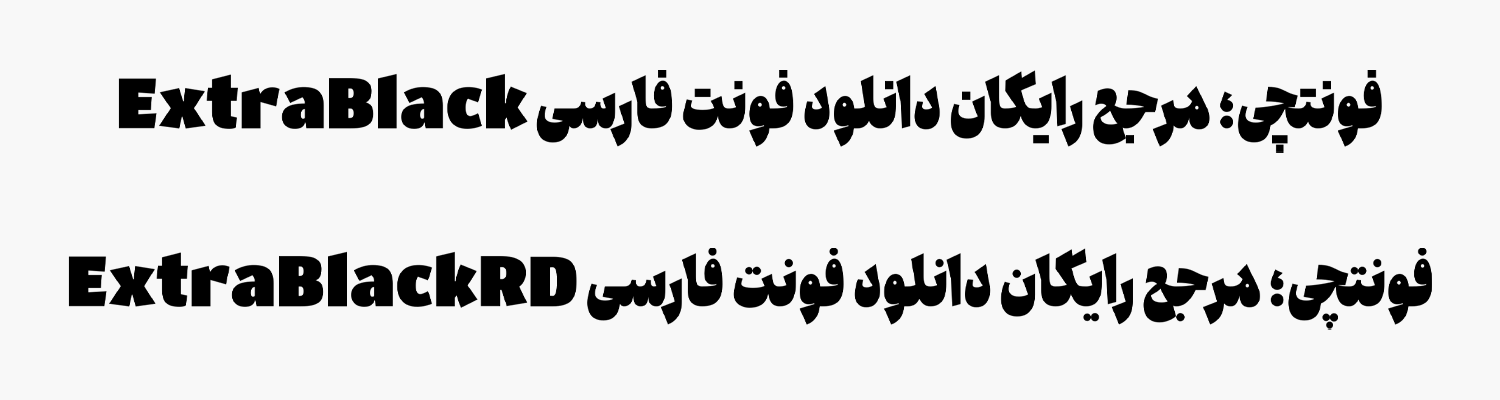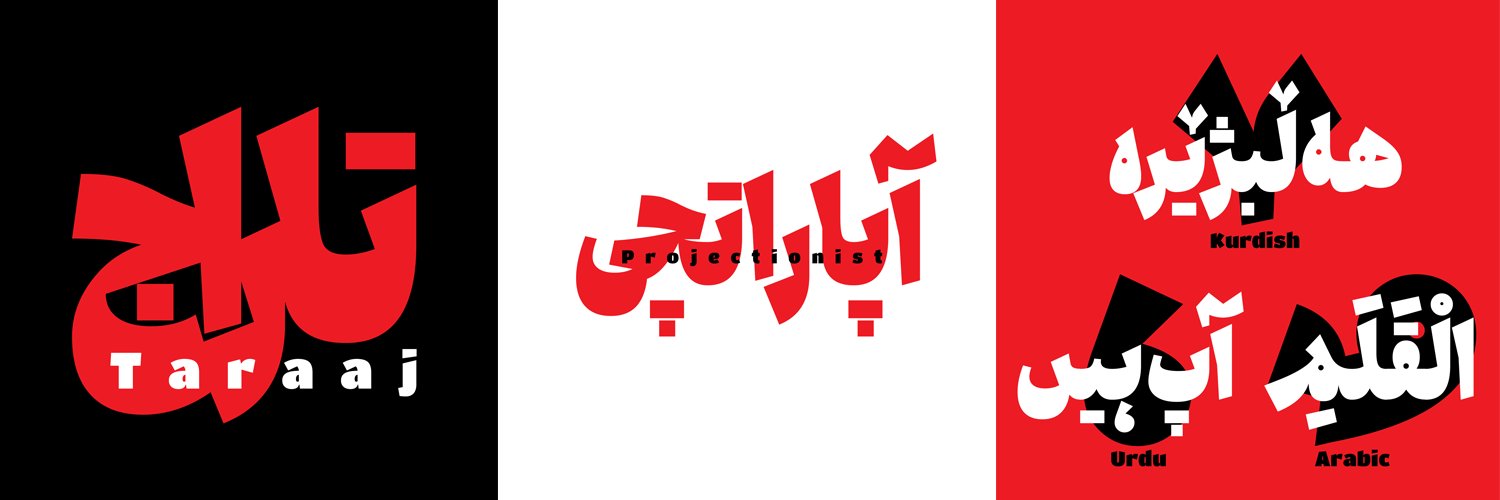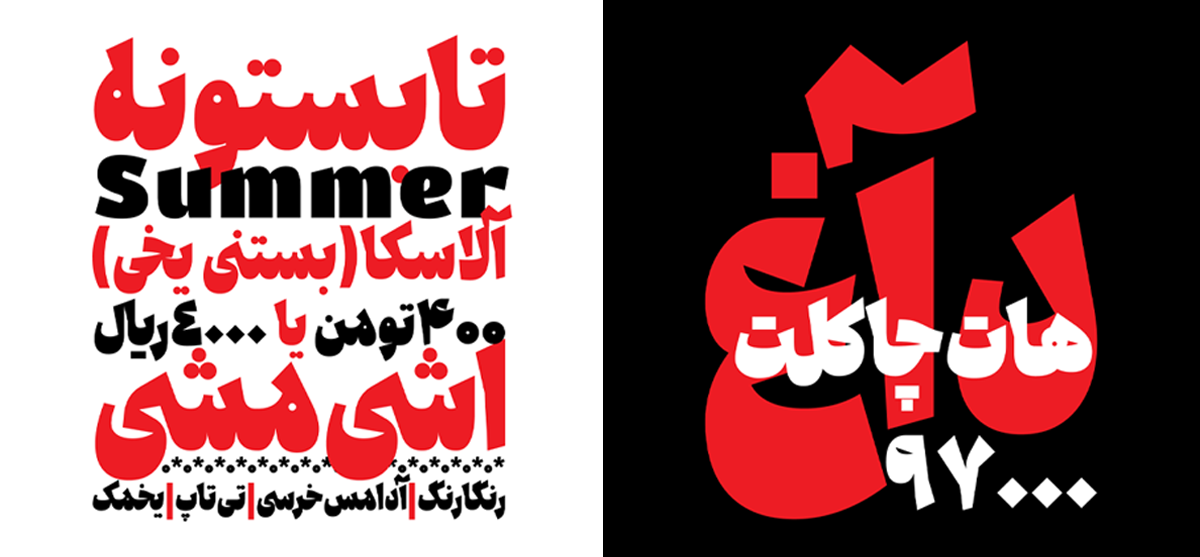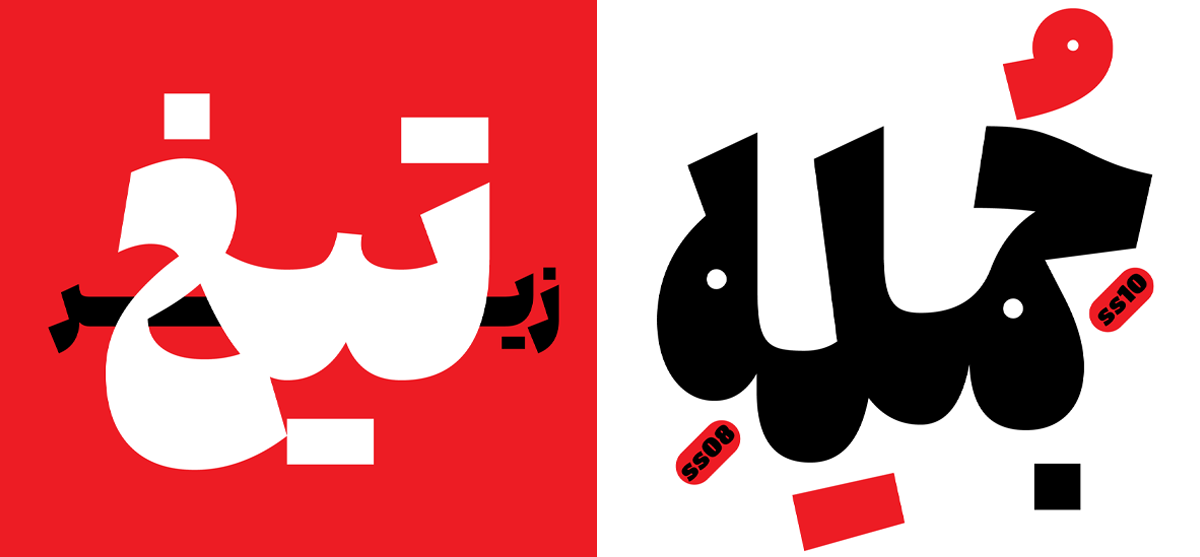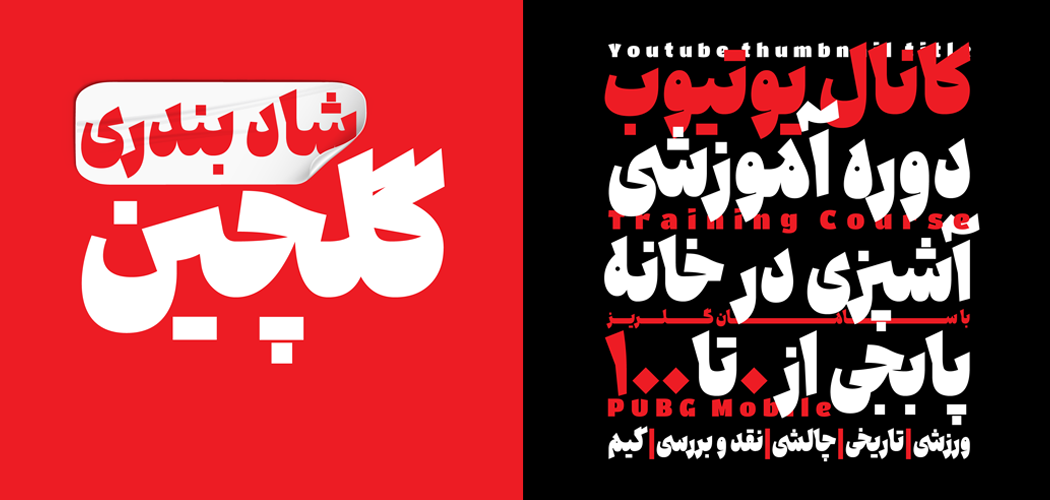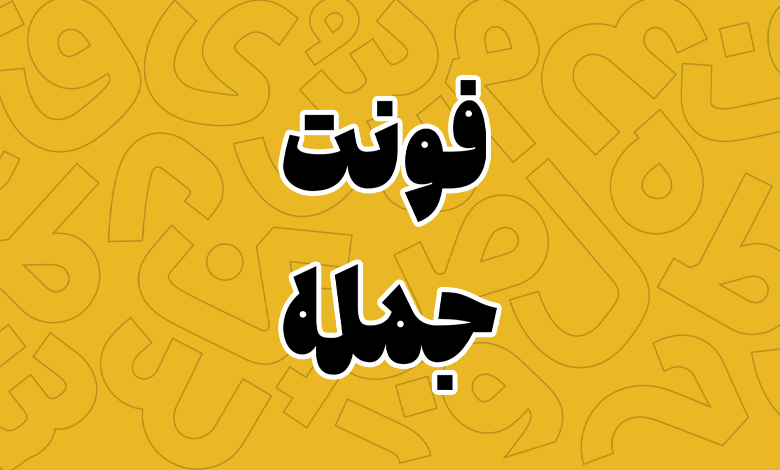
فونت جمله (Jomleh)
فونت جمله (به انگلیسی: Jomleh) از سری فونتهای فانتزی قدیمی به سبک دهه ۵۰ است که با ترکیبی از هندسه، آزادی در طراحی و البته اندکی اغراق طراحی شده که ترکیبی از تیزی و ساختار منحنی را در این فونت ایجاد کرده است. فونت جمله رایگان نیست و در یک وزن با دو سبک نقطهگذاری طراحی شده است.
سعید حقیقت این فونت را به عنوان یک فونت نمایشی برای استفاده در عناوین، جملات کوتاه، پوسترها و تبلیغات طراحی کرده است که با ظاهر صمیمی خود به طرحهای شما ظاهری متفاوت و نوستالژیک خواهد بخشید. در ادامه با نقد و بررسی کاملتری از امکانات این فونت همراه باشید.
معرفی و دانلود فونت جمله (Jomleh) سبک فانتزی
فونت جمله فارسی محدود به این زبان نبوده و از دیگر زبانهای عربی، کردی و اردو نیز پشتیبانی کامل و استانداردی دارد. برای زبان انگلیسی نیز از فونت اپن سورس TitanOne استفاده شده است که همین سبک را در فونت تداعی میکند.
بخش اعداد در این فونت کاملا استاندارد طراحی شده است. اعداد عربی «۰۴۵۶» گلیف استاندارد خود را دارند و از اعداد فارسی «۰۴۵۶» در آنها استفاده نمیشود. برای زبان اردو نیز همین مسئله صدق میکند.
سبک طراحی و وزن فونت جمله
ایده طراحی فونت جمله از حرف «ـه» شکل گرفته است که فرم آن به دو بخش تیز در بخش بیرونی و منحنی در چشمی تبدیل شده است. همین ایده برای تمامی حروف اجرا شد تا فونت در دو سبک نقطه گرد و عادی طراحی شود.
این فونت دارای وزن فوق سنگین Extra Black است که میتوان در عناوین و متون کوتاه از آن استفاده کرد. روشن است که استفاده از این فونت در بدنه و برای متون طولانی کاربردی نیست.
طراح این فونت تلاش کرده که حروف تا حد ممکن متفاوت طراحی شوند تا یک فونت تیتر جذاب نیمه فانتزی و در عین حال خوانا داشته باشیم. پوستر فیلم و سریال، تیتر مطالب تبلیغاتی و تولید محتوا در رسانههای اجتماعی بخشی از کاربردهای این فونت زیبا است.
ترکیبات و حروف جایگزین متنوع
در فونت جمله شاهد استفاده حروف و ترکیبات جایگزین به شکلی متفاوت از بیشتر فونتها هستیم. جدای از ترکیبات تکی و دوتایی، شاهد استفاده از ترکیبات سهتایی برخی حروف به عنوان جایگزین هستیم.
این ترکیبات دست شما را باز میگذارد تا در طراحی حروفی که جنبه نمایشی یا تبلیغاتی دارند، با تایپ متفاوت آنها نرخ نمایش و تبدیل را افزایش دهید. به گفته طراح در آینده نیز ترکیبات بیشتری به این حروف افزوده خواهد شد.